Lựa chọn font chữ thiết kế poster sai lầm có thể khiến thông điệp bị lu mờ, poster trở nên khó đọc, thiếu chuyên nghiệp, hoặc thậm chí là truyền tải sai lệch cảm xúc. Ngược lại, việc nắm vững cách chọn và sử dụng font chữ sẽ giúp poster của bạn nổi bật, dễ dàng tiếp cận và đạt được hiệu quả truyền thông tối đa.
Bài viết này sẽ đưa bạn đi sâu vào thế giới của font chữ trong thiết kế poster, khám phá tầm quan trọng đặc thù của chúng, giới thiệu các loại font phù hợp, chia sẻ những nguyên tắc lựa chọn và sử dụng font hiệu quả trên poster, cũng như gợi ý các nguồn tìm kiếm font chất lượng. Hãy cùng tìm hiểu cách để font chữ làm cho poster của bạn trở nên sống động và thu hút hơn bao giờ hết!
Các loại Font chữ lý tưởng dùng trong thiết kế Poster
Font chữ là nền tảng của thiết kế poster hiệu quả. Dưới đây là những loại font phổ biến và lý tưởng nhất.
Font Display / Decorative (Font Trang Trí):
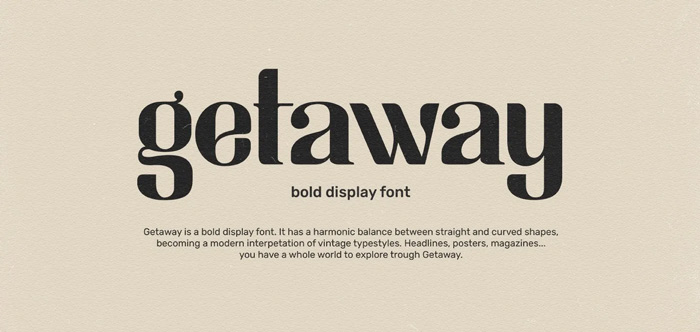
Đặc điểm: Được thiết kế đặc biệt để nổi bật ở kích thước lớn. Thường có phong cách độc đáo, mạnh mẽ, cá tính, và rất đa dạng về hình thức.
Tại sao phù hợp cho poster: Đây chính là "ngôi sao" cho các tiêu đề chính (headline) trên poster. Khả năng thu hút thị giác mạnh mẽ của font display cho poster giúp thông điệp chính của bạn "nhảy" ra khỏi trang và ngay lập tức gây ấn tượng. Chúng thiết lập không khí và phong cách tổng thể cho poster nhanh chóng.
Lưu ý: Thường chỉ dùng cho tiêu đề hoặc một vài từ khóa quan trọng. Hầu như không bao giờ dùng cho đoạn văn bản dài vì khó đọc ở kích thước nhỏ.
Font Sans-serif (Font Không Chân):
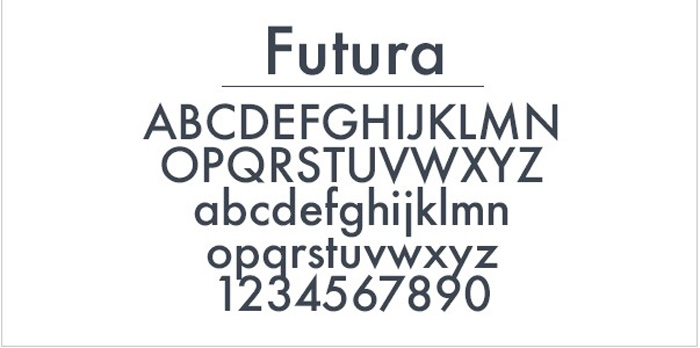
Đặc điểm: Gọn gàng, hiện đại, không có "chân". Có nhiều biến thể về độ đậm nhạt và chiều rộng.
Tại sao phù hợp cho poster: Các font Sans-serif đậm, in hoa hoặc có nét độc đáo một chút rất hiệu quả cho tiêu đề phụ hoặc các thông tin quan trọng cần dễ đọc nhanh. Font sans-serif cho poster cung cấp sự rõ ràng và dễ đọc, đặc biệt các phiên bản geometric hoặc grotesque có thể tạo cảm giác mạnh mẽ, hiện đại. Chúng cũng là lựa chọn tuyệt vời cho các đoạn văn bản nhỏ hơn nhờ tính dễ đọc trên nhiều kích thước.
Ví dụ ứng dụng: Tiêu đề phụ, tên nghệ sĩ/diễn giả, ngày tháng, địa điểm.
Font Slab Serif (Font Chân Dày)
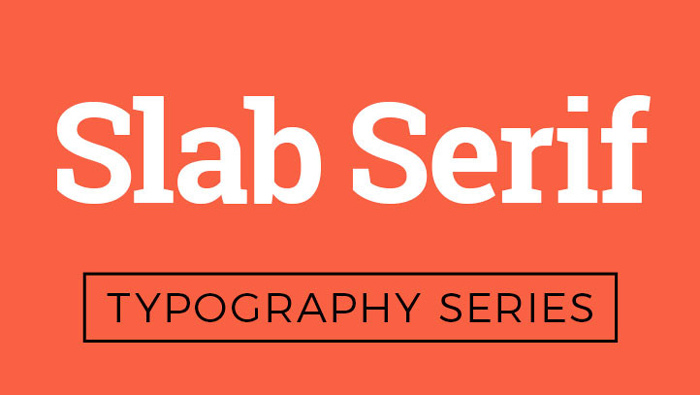
Đặc điểm: Font Serif với phần chân rất dày và nổi bật, tạo cảm giác rắn rỏi, mạnh mẽ.
Tại sao phù hợp cho poster: Sự "nặng ký" của font slab serif poster làm cho chúng trở thành lựa chọn tuyệt vời cho các tiêu đề cần sự nhấn mạnh, đáng tin cậy hoặc có hơi hướng vintage/công nghiệp. Chúng rất dễ đọc ở kích thước lớn.
Font Serif (Font Chân)
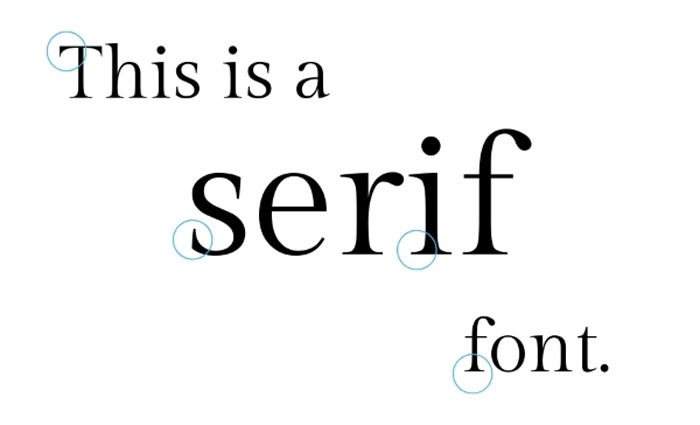
Đặc điểm: Có "chân" ở cuối ký tự, đa dạng từ cổ điển đến hiện đại.
Tại sao phù hợp cho poster: Các font Serif có độ tương phản cao (Modern Serif) hoặc các font Serif đậm, có cá tính có thể dùng cho tiêu đề để tạo vẻ sang trọng, cổ điển hoặc độc đáo. Các font Serif truyền thống, dễ đọc cũng có thể dùng cho các đoạn thông tin chi tiết (body text) nếu không gian cho phép và phong cách poster phù hợp.
Font Script (Font Viết Tay/Thư Pháp)
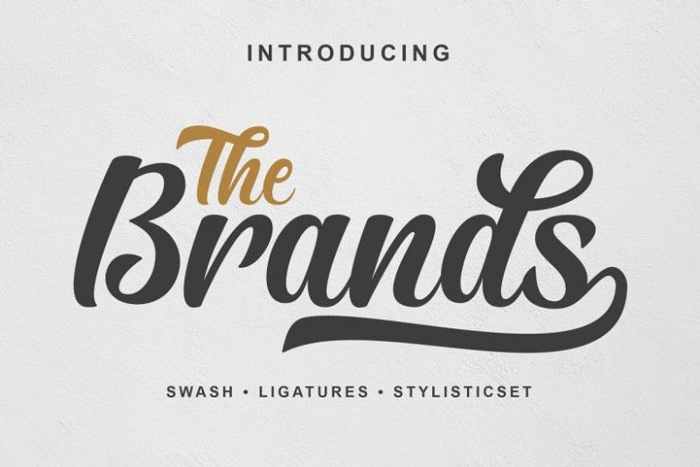
Đặc điểm: Mô phỏng chữ viết tay, bay bổng, mềm mại hoặc cá tính mạnh.
Tại sao phù hợp cho poster: Thường được sử dụng như một điểm nhấn nghệ thuật ở tiêu đề hoặc một vài từ quan trọng để thêm nét cá nhân, sang trọng hoặc bay bổng. Font script poster cần được dùng rất cẩn trọng, đảm bảo vẫn dễ đọc ở kích thước sử dụng và không làm rối mắt.
Kết hợp các loại font này một cách khéo léo sẽ giúp bạn tạo ra một poster có hệ thống thông tin rõ ràng, thu hút và truyền tải đúng phong cách font poster mong muốn.
Một số Font chữ nổi bật thường dùng cho Poster
Dưới đây là một vài cái tên thường được các designer tin dùng cho poster, thuộc các loại khác nhau:
- Bebas Neue (Sans-serif Condensed): Mạnh mẽ, in hoa, gọn gàng, hiện đại. Rất phổ biến cho tiêu đề poster cần sự "đanh thép" và tiết kiệm không gian. (Miễn phí)
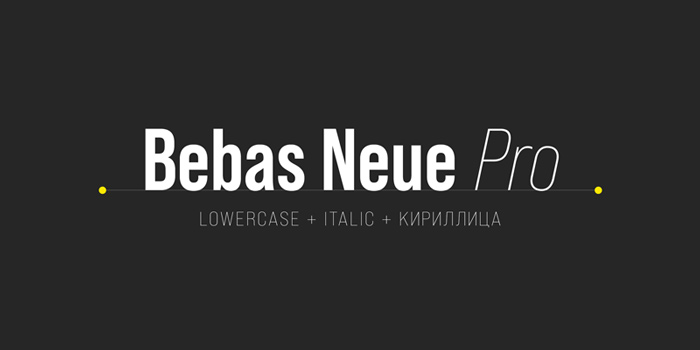
- Oswald (Sans-serif Condensed): Tương tự Bebas Neue, nhưng có nét mềm mại hơn một chút. Dễ đọc và hiệu quả cho tiêu đề hoặc tiêu đề phụ. (Miễn phí)
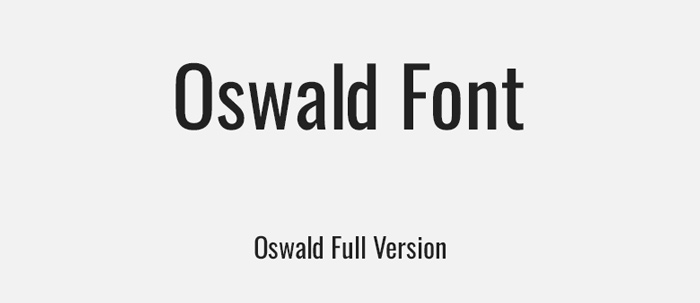
- Montserrat (Sans-serif): Như đã nói ở bài logo, Montserrat rất linh hoạt. Phiên bản Black hoặc Bold của nó cực kỳ phù hợp cho tiêu đề poster, trong khi các phiên bản Light/Regular dùng tốt cho nội dung chi tiết. (Miễn phí)
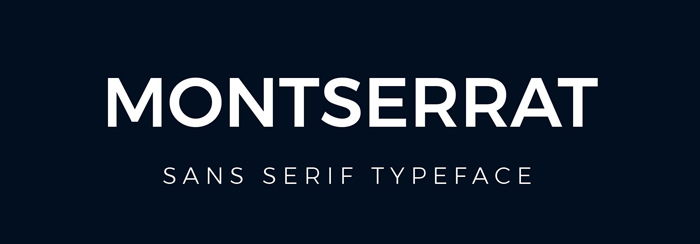
- Anton (Sans-serif Extra-bold): Rất đậm và cao, tạo hiệu ứng thị giác mạnh mẽ. Lý tưởng cho các poster cần font tiêu đề "đập vào mắt". (Miễn phí)
- Playfair Display (Serif): Phiên bản Display của Serif này có nét tương phản cao, mang lại vẻ sang trọng, kịch tính hoặc cổ điển cho tiêu đề poster (ví dụ: poster phim, sự kiện văn hóa). (Miễn phí)
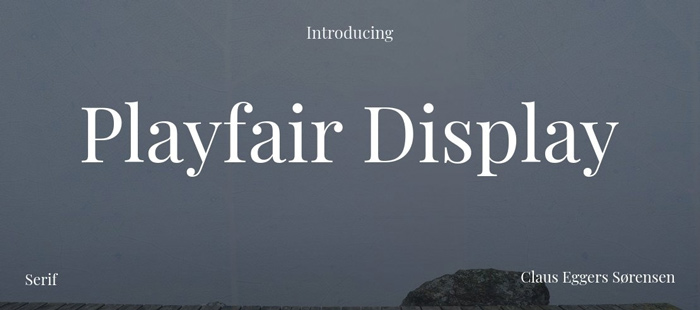
- ChunkFive (Slab Serif): Một font Slab Serif đậm, vuông vắn, tạo cảm giác retro, mạnh mẽ, đáng tin cậy. Tuyệt vời cho tiêu đề poster cần sự chắc chắn. (Miễn phí)
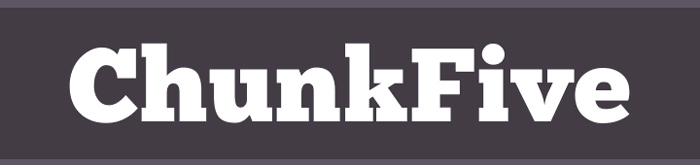
Nguyên tắc sử dụng Font chữ trong bố cục Poster
Cách kết hợp các Font chữ hài hòa để tạo ra một poster chuyên nghiệp và dễ đọc. Đây là những nguyên tắc cốt lõi khi sử dụng font chữ thiết kế poster:
Tránh những lỗi thường gặp khi sử dụng font chữ trên poster này sẽ giúp bạn tạo ra những ấn phẩm thu hút, chuyên nghiệp.
Hãy mạnh dạn thử nghiệm các font khác nhau, quan sát cách các poster thành công sử dụng font chữ, và luôn đặt câu hỏi liệu font chữ bạn chọn đã phục vụ tốt nhất cho mục tiêu của poster hay chưa.